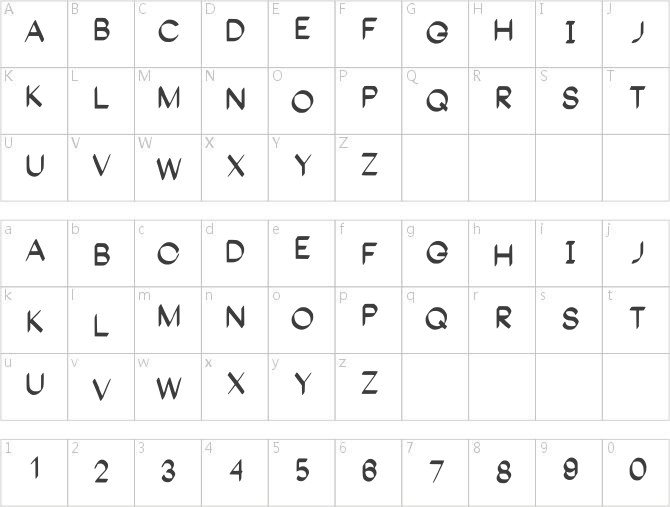
字體名稱: Gangnam
Gangnam
Gangnam介紹
Gangnam字體字庫(kù)是一款讓人賞心悅目、百看不厭的英文字體,適合各類廣告和產(chǎn)品包裝設(shè)計(jì)應(yīng)用,字體大小0.02MB,格式為ttf字體,上傳用戶是g05662,作者/版權(quán)方為未知
Gangnam效果圖